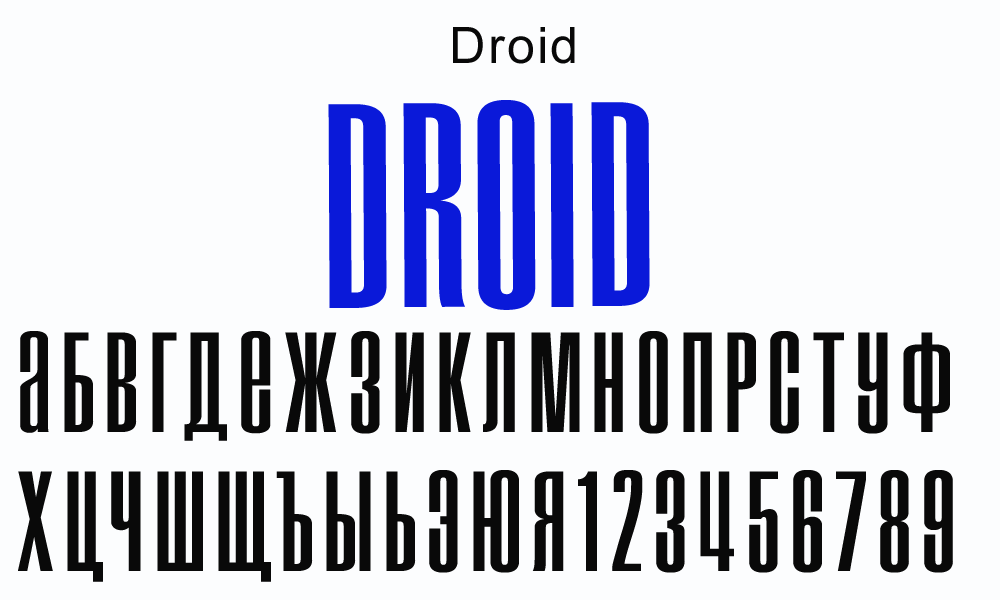
В то время как Monotype Design Studios разработала Binner Gothic около 1900, разработанный Grotesque, тем не менее, имеет очень современный вид. В верхнем регистре чрезвычайно высокая медиана усиливает очень высокий характер чрезвычайно узких букв.